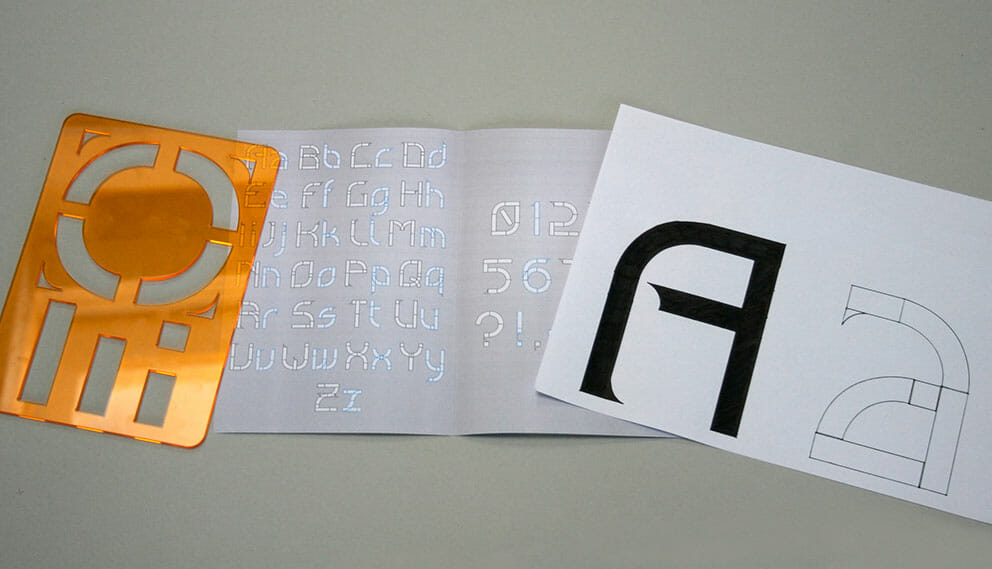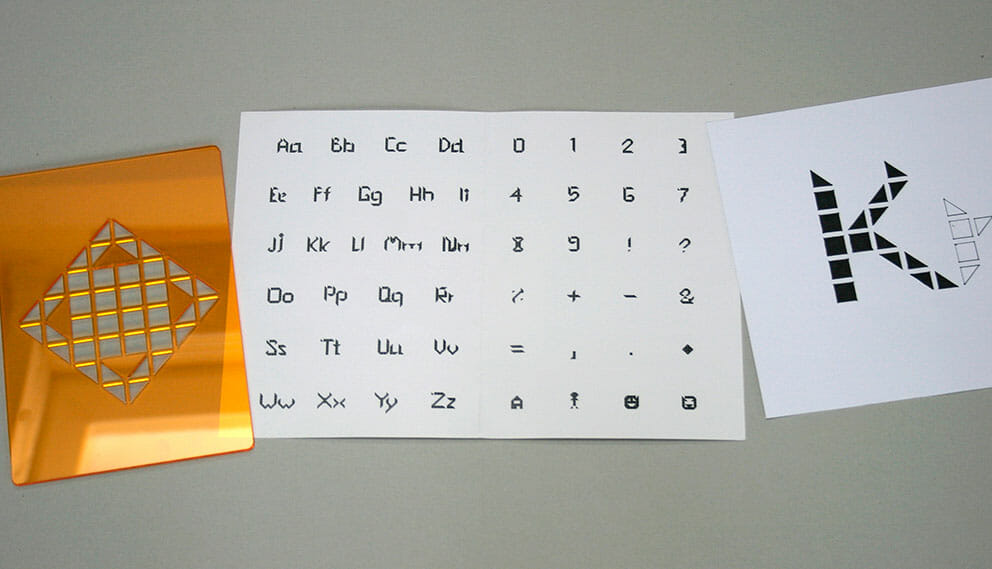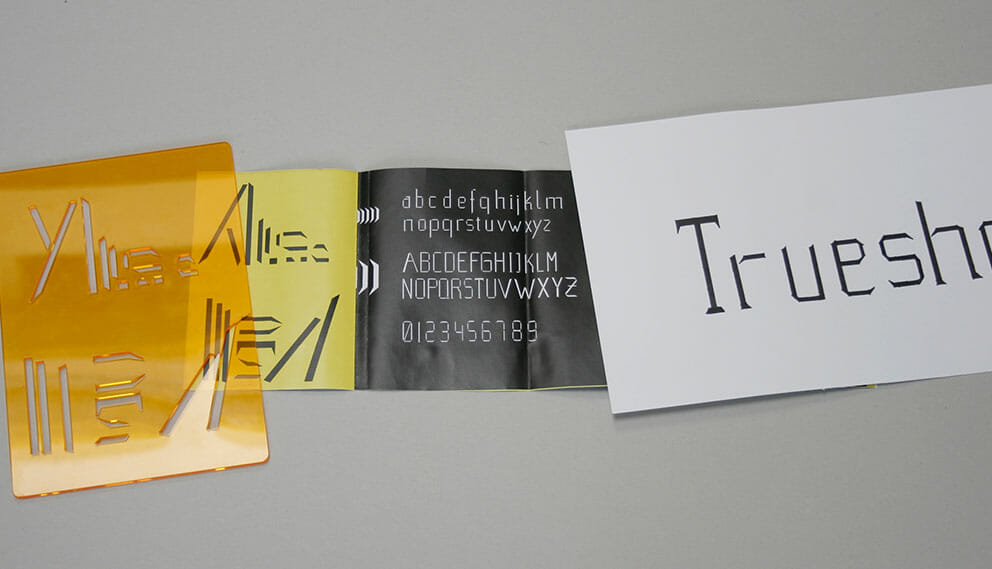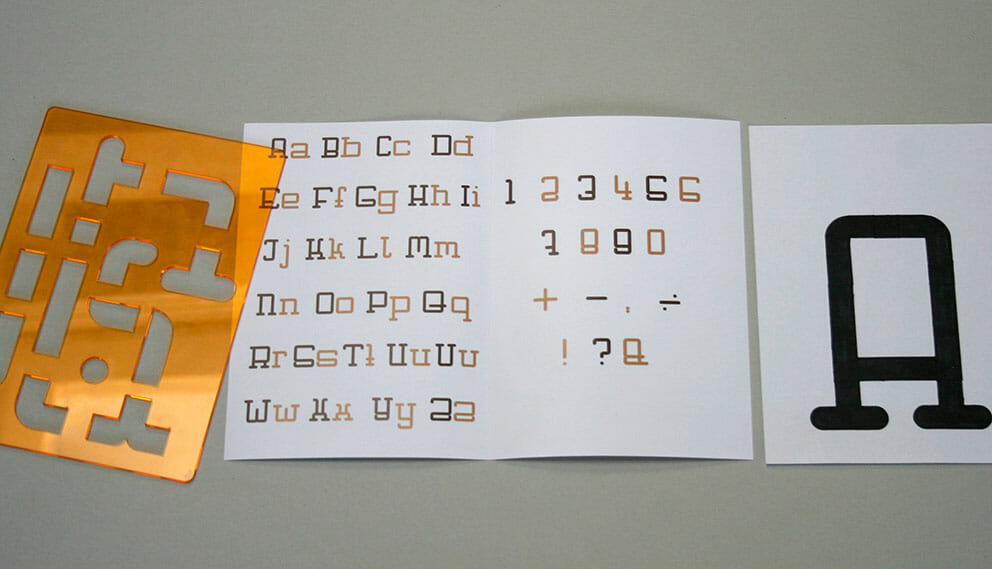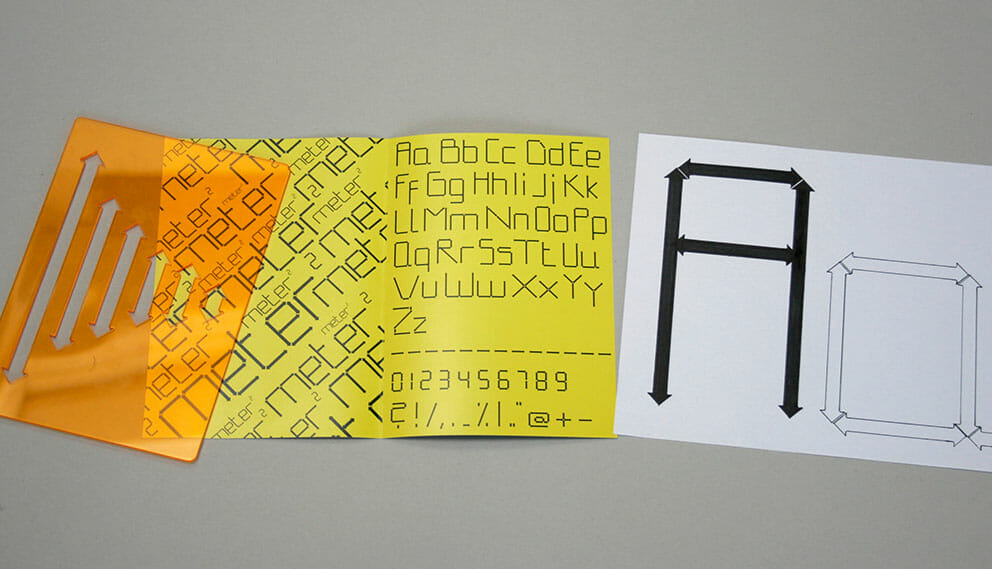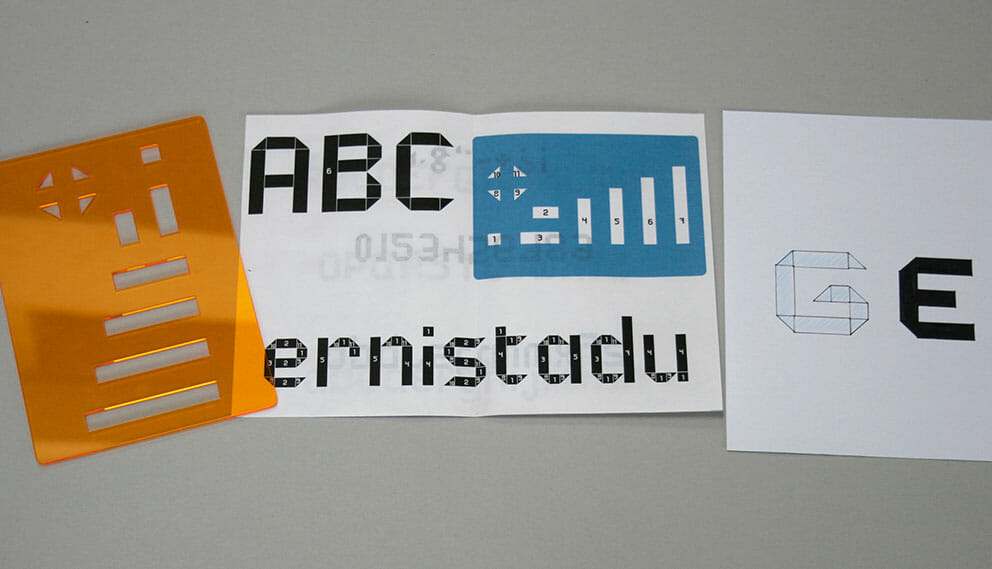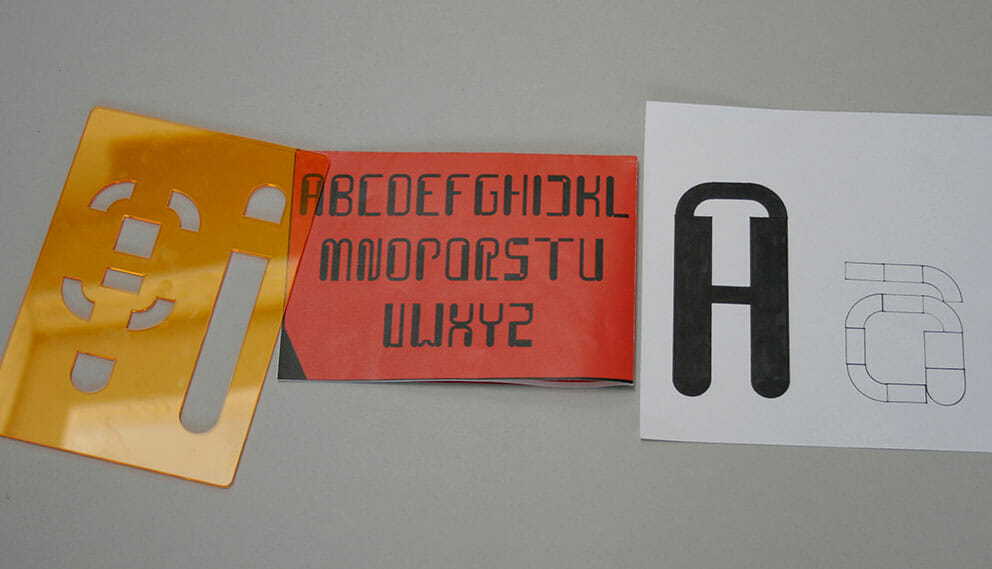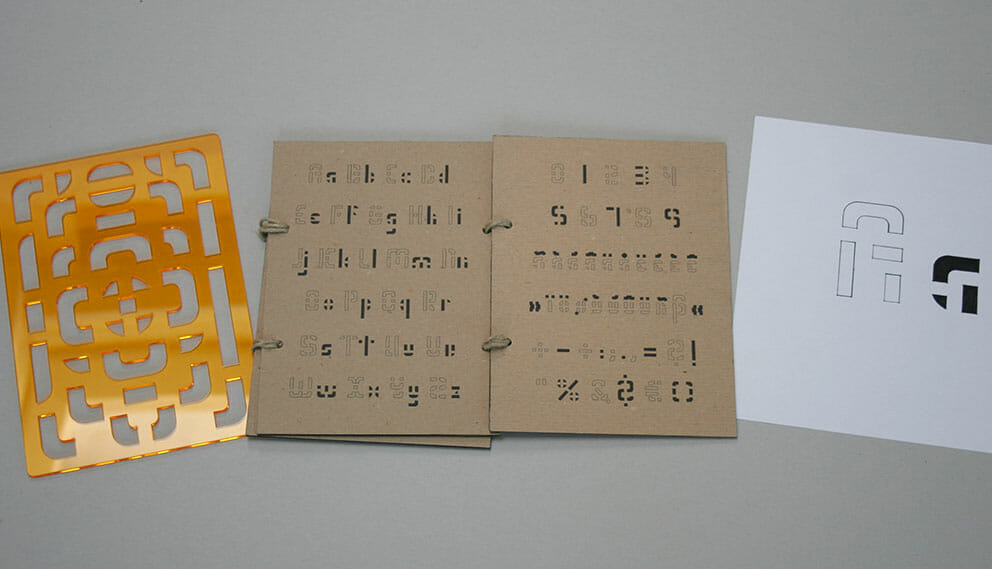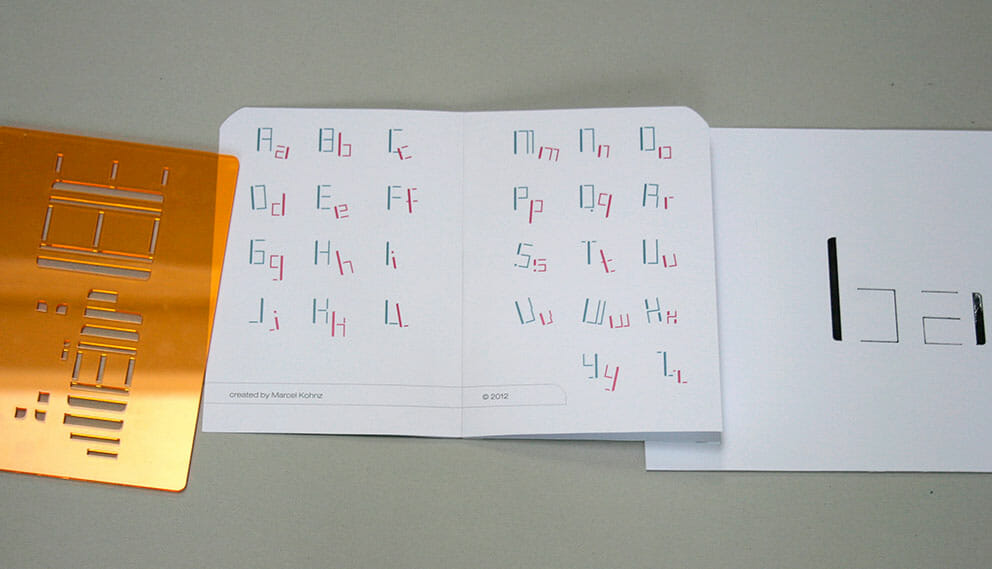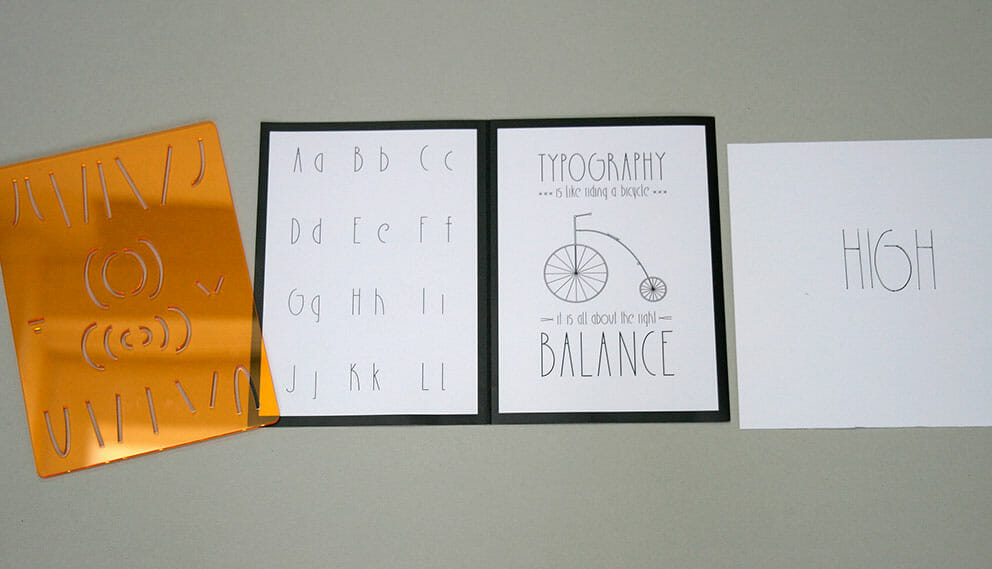
Schriftentwurf und Schablone
Aufgabe:
Konzeption und Entwurf einer Schrift auf Basis der Reihung von wenigen gleichen Modulen.
Zum jeweiligen Schriftentwurf wurde eine Anleitung und eine Schablone in A5 gefertigt.
“Circle Dragon” – Christina Kraus
“Androindi” – India Uhlig
“Howl” – Jakob Buraczewski
“Kapua” – Jasmin Maier
“Plex” – Jessica Sapper
“Typografie” – Julian Reich
“High Wheeler” – Marc Benzel
“Bad Day” – Marcel Kohnz
“Pieces” – Maritta Hinterseh
“Brighton Rock” – Marius Jacob
“Geot” – Matthias Ley
“Meter2” – Philipp Sommer
“Sheriff Serif” – Pia Spieler
“Get It Simple” – Readone Mohamed
“Virgule” – Sebastian Schreck
“CirclePit” – Stefanie Kraemer
“Trueshot Barrage” – Thomas Christ
“Belial” – Timm Dreyer
“Kreck” – Tobias Borns
“Focus Waves” – Victor Steinbach
Storm – Julia Goerke